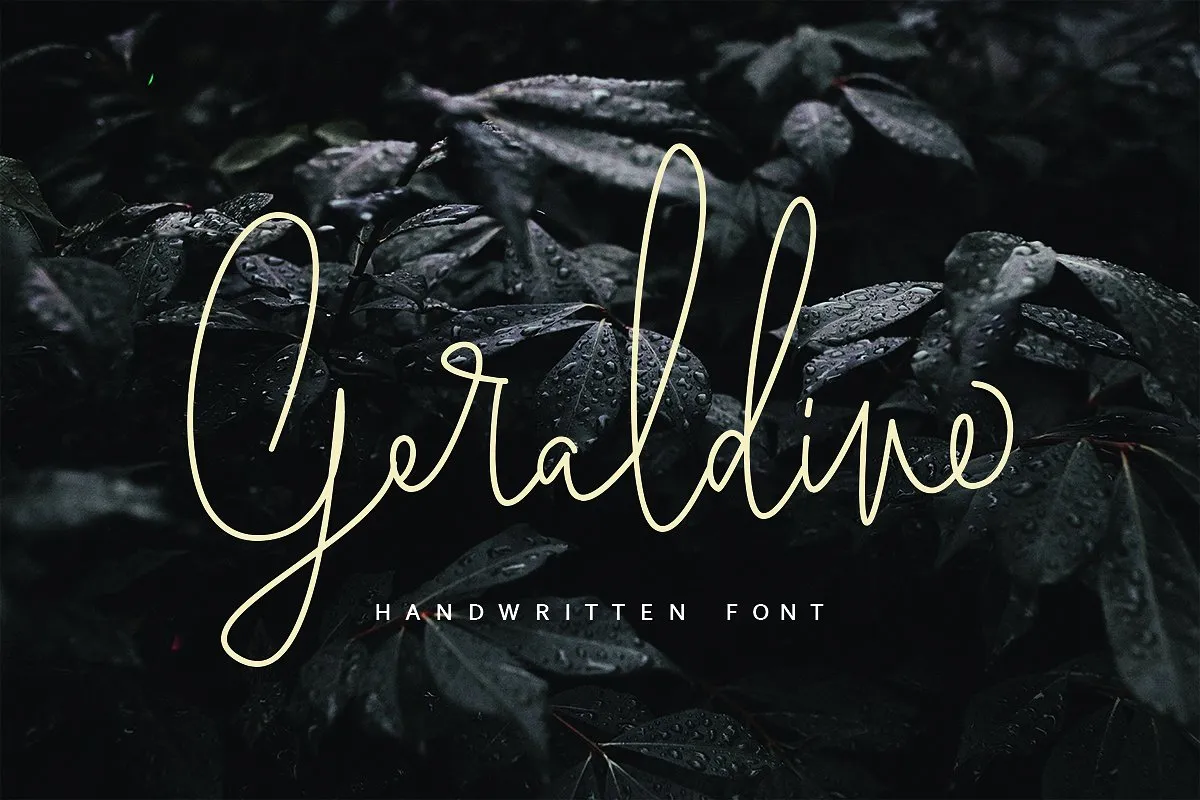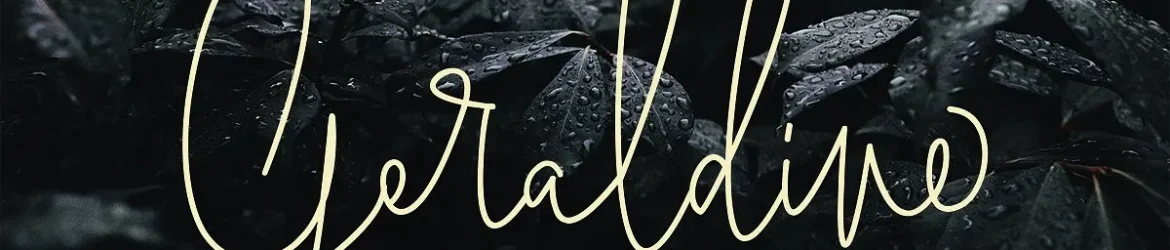
Geraldine Handwritten Font – Download Grátis
Geraldine é uma elegante tipografia feita à mão que combina a delicadeza do script com a funcionalidade prática das fonts modernas. Desenvolvida e compartilhada pela Geranium.Co, Geraldine é perfeita para estilos de texto envolventes como marcas de marca, cartões de aniversário, embalagens fashion e outros projetos que exigem um toque pessoal. A característica mais apreciada da fonte é a maneira com que cada letra foi meticulosamente criada. Geraldine oferece uma aparência encantadora e única para qualquer projeto em que ela seja aplicada, seja ele um logotipo ou um post-it de aniversário. Com sua rica farta gama de estilos, Geraldine é perfeita para projetos variados como cartazes, marcas de marca, vestuário fashion, convites e até mesmo para criar uma assinatura única em suas peças de escrita. Com seu estilo script moderno, esta fonte criativa irá transformar qualquer projeto em um trabalho de arte. Geraldine é uma ótima escolha tanto para os iniciantes quanto para os profissionais da design visual que buscam dar um toque pessoal e artístico aos seus projetos. E isso sem dúvida o torna uma excelente fonte para colecionadores e entusiastas do design de letras.